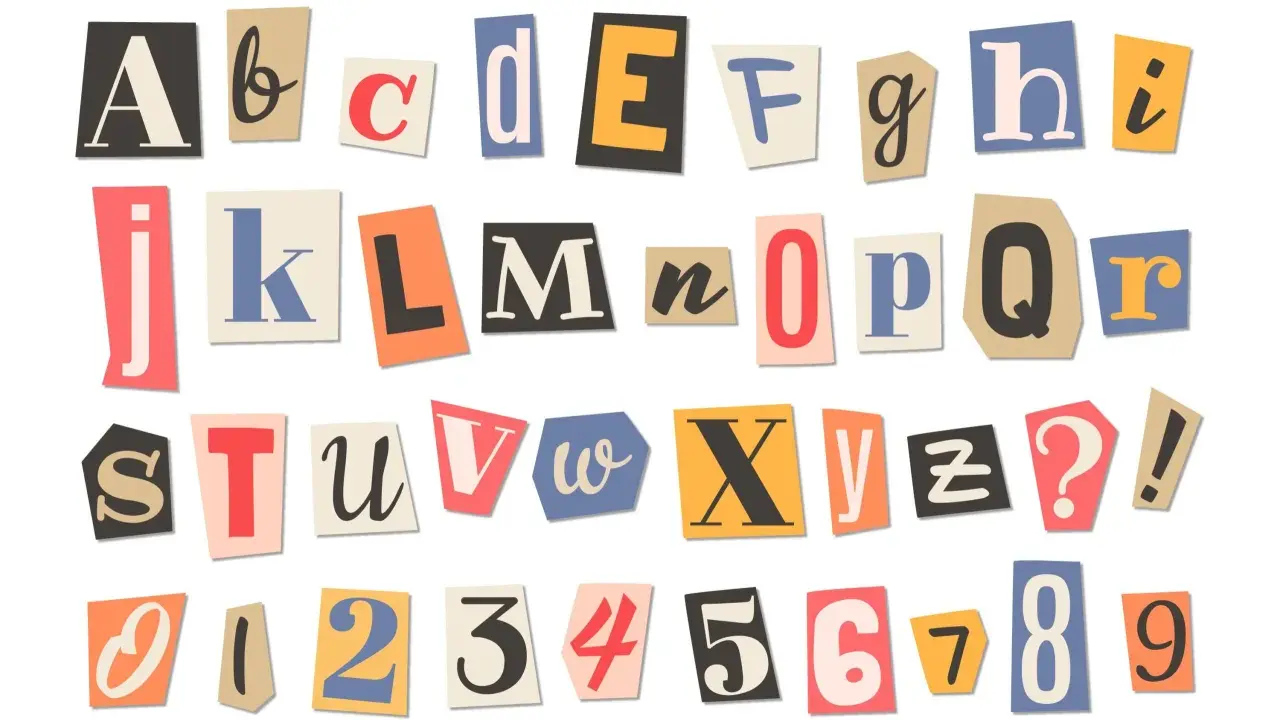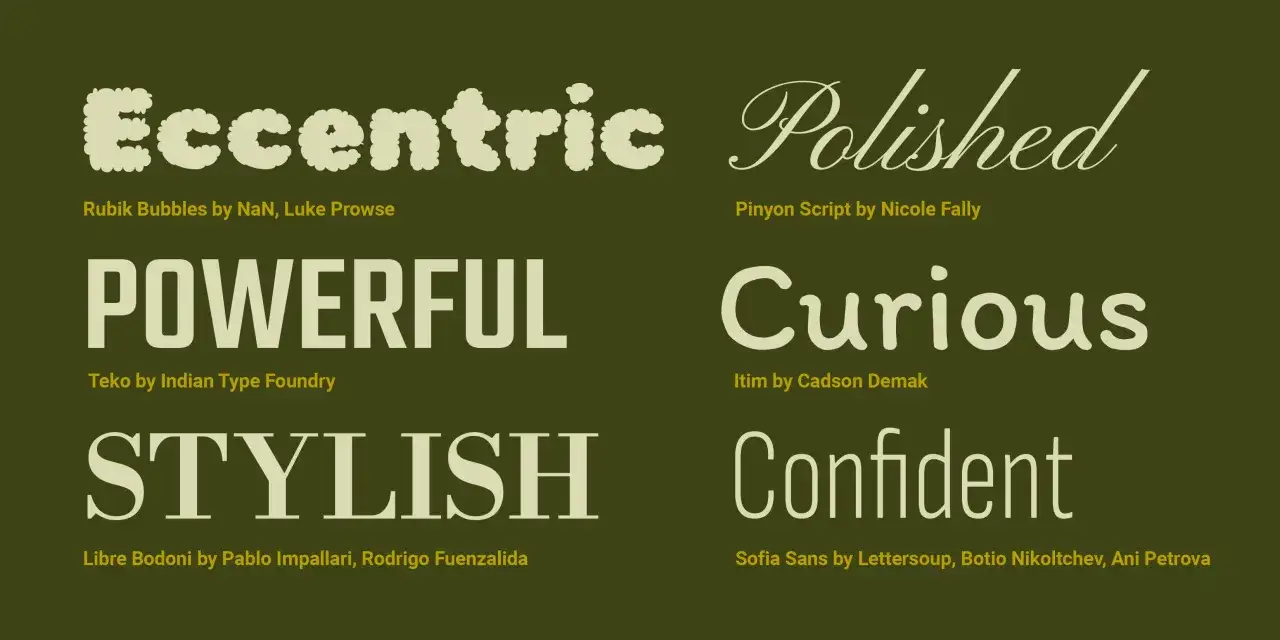
Czcionki do pisania - Jak wybrać i łączyć, by projekt zachwycał?
Kolekcja wyciętych z gazet liter i cyfr, tworząca alfabet i liczby. Idealne czcionki do pisania tajnych wiadomości.
Odręczne kroje potrafią dodać projektowi ciepła, charakteru i odrobiny ludzkiego śladu, ale tylko wtedy, gdy są dobrane świadomie. W praktyce chodzi o czcionki do pisania, które wyglądają naturalnie na ekranie, pasują do celu projektu i nie psują czytelności. Poniżej pokazuję, jak odróżnić dobry font od dekoracyjnej pułapki, kiedy sięgnąć po styl pisma odręcznego i jak łączyć go z resztą typografii.
Najlepszy font odręczny to ten, który wspiera treść, a nie ją przykrywa
• Fonty odrębne od tekstu głównego najlepiej działają w nagłówkach, cytatach, logo i krótkich hasłach.
• W dłuższych akapitach lepiej sprawdzają się proste kroje bezszeryfowe lub klasyczne szeryfy.
• Przed użyciem sprawdzam polskie znaki, odstępy między literami i czytelność w rozmiarze 16 px.
• Jedna ozdobna rodzina na projekt zwykle wystarcza; dwie dekoracyjne naraz najczęściej robią chaos.
• Na ekranie telefonu odręczne fonty działają najlepiej jako akcent, nie jako podstawowy tekst.
Kiedy font odręczny ma sens, a kiedy lepiej odpuścić
Ja traktuję takie kroje jak przyprawę. Dają charakter, ale w nadmiarze dominują nad treścią. Najlepiej sprawdzają się w nagłówkach, cytatach, zaproszeniach, brandingach lifestyle, opakowaniach i krótkich komunikatach, gdzie potrzebny jest ton bardziej osobisty niż neutralny.
Jeśli projekt ma być przede wszystkim informacyjny, dekoracyjny skrypt szybko zaczyna przeszkadzać. W długich akapitach lepszy będzie prostszy krój, a odręczny font można zostawić na jeden akcent: tytuł, podpis, nazwę kolekcji albo krótkie hasło.
To prowadzi do ważniejszego pytania: po czym poznać, że dany font nie tylko wygląda ciekawie, ale też naprawdę działa.
Jak oceniam, czy dany krój będzie czytelny
Nie patrzę wyłącznie na pierwsze wrażenie. W praktyce liczy się kilka rzeczy, które bardzo szybko zdradzają, czy font nadaje się do realnego użycia, czy tylko dobrze wygląda na podglądzie.
• Wysokość małych liter - im wyższa, tym zwykle łatwiej czytać tekst na ekranie. Wysokość x to po prostu wysokość liter bez wydłużeń, na przykład „a” czy „e”.
• Odstępy między znakami - zbyt ciasny font wygląda efektownie przez chwilę, ale męczy wzrok. Jeśli litery zaczynają się zlewać, to zły znak.
• Polskie znaki - w projekcie po polsku obowiązkowo sprawdzam ą, ć, ę, ł, ń, ó, ś, ź i ż. Brak diakrytyków dyskwalifikuje font szybciej niż cokolwiek innego.
• Ligatury - to specjalnie połączone pary liter, na przykład „fi” albo „st”. Mogą wyglądać świetnie, ale w nadmiarze robią z tekstu ozdobę zamiast narzędzia.
• Wagi i odmiany - jeśli rodzina ma tylko jedną bardzo cienką wersję, jej użycie bywa ryzykowne. Trochę większa elastyczność daje więcej kontroli.
• Czytelność w małej skali - font, który wygląda dobrze na dużym podglądzie, może kompletnie rozsypać się przy 16 px.
W praktyce robię prosty test: wpisuję 2-3 zdania, ustawiam rozmiar 16 px i patrzę, czy po kilku sekundach nadal czytam treść bez wysiłku. Jeśli nie, traktuję ten krój jako dekoracyjny, a nie użytkowy. A gdy już wiem, że czytelność się broni, przechodzę do stylów i konkretów.
Różnorodne czcionki do pisania: Eccentric, Polished, Powerful, Stylish, Curious, Confident.
Jakie style najlepiej działają w praktyce
W katalogach fontów, także w Google Fonts, najczęściej wracam do kilku rodzin, bo po prostu dobrze rozwiązują różne problemy. Każda z nich daje inny efekt, więc warto patrzeć nie tylko na nazwę, ale przede wszystkim na to, jaki ton komunikuje projekt.
Styl Kiedy go użyć Największa zaleta Ryzyko Przykłady
Casual handwriting Blogi, notatki, cytaty, UI, krótkie podpisy Naturalny, lekki i „ludzki” charakter Może wyglądać zbyt swobodnie w projekcie premium Patrick Hand, Gochi Hand, Shadows Into Light
Formal script Zaproszenia, beauty, moda, luksusowe marki Elegancja i płynność ruchu Szybko traci czytelność w dłuższych tekstach Great Vibes, Pinyon Script, Style Script
Marker i brush Plakaty, social media, hasła promocyjne Energia i mocny, wyrazisty ton Łatwo przesadzić z agresją wizualną Permanent Marker, Just Another Hand
Minimal handwriting Minimalistyczne projekty, light branding, edukacja Subtelność i prosty, nienachalny efekt Nie daje efektu „wow”, jeśli projekt potrzebuje mocnego akcentu Kalam, Reenie Beanie, Amatic SC
Fonty edukacyjne Workbooki, materiały dla dzieci, ćwiczenia pisma Równy rytm liter i dobra struktura znaków Nie zawsze pasują do projektów komercyjnych Playwrite, Playwrite USA Modern, Playwrite Norge
Jeśli projekt jest po polsku, nie kończę wyboru na samym wyglądzie. Sprawdzam też, czy krój dobrze obsługuje litery diakrytyczne i czy nie rozjeżdża się interpunkcja, bo to właśnie takie detale odróżniają gotowy projekt od wersji „prawie dobrej”. Kiedy styl jest już wybrany, trzeba jeszcze połączyć go z resztą typografii, żeby całość nie zaczęła się gryźć.